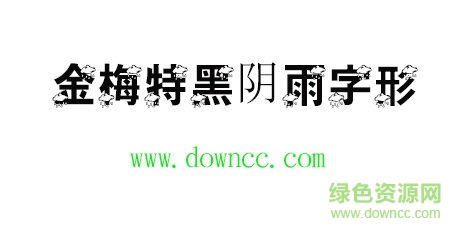
金梅特黑陰雨字形是一款偏卡通風(fēng)的繁體字體,此款字體每個(gè)字上面都有一朵云彩,字形片粗,具有影人注目的效果,應(yīng)用范圍也比較廣泛,適合做特殊廣告平面設(shè)計(jì)的朋友使用,而且還是永久免費(fèi)的哦,喜歡的朋友歡迎來(lái)綠色資源網(wǎng)下載!
1.完全支持日文、韓文、繁體中文和簡(jiǎn)體中文。
2.筆形方頭方尾、黑白均勻。